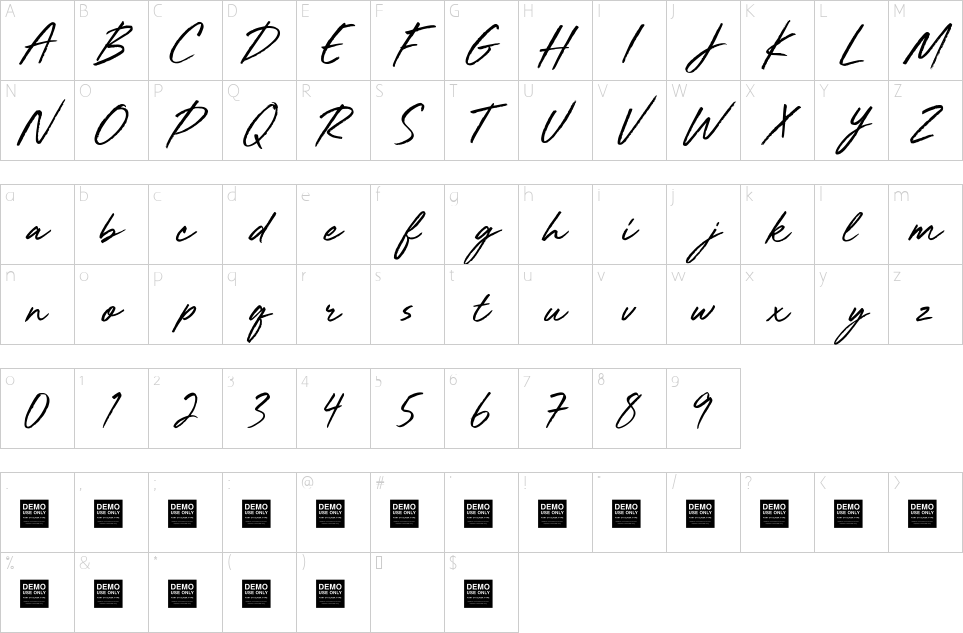
Descubra a beleza natural e fluida da fonte Mighty River, uma opção ideal para seus projetos gráficos. Desenhada por BLKBK Fonts, essa fonte é uma excelente escolha para quem busca um equilíbrio entre elegância e facilidade de uso. Desenvolvida especialmente para Windows e Mac, Mighty River oferece um conjunto de caracteres detalhado e fluido que vai desde letras leves e delicadas até mais robustas e autoritárias. Com seu design cuidadosamente pensado, essa fonte traz um toque de criatividade para qualquer projeto, seja em uma newsletter ou em um layout de site. Com um design fluido que flui como o próprio rio Mighty, essa fonte traz uma essência natural que encaixa-se perfeitamente em qualquer estilo de design. Desfrute da beleza da Mighty River, uma fonte gráfica única, disponível para quem busca um estilo inovador em seus projetos.